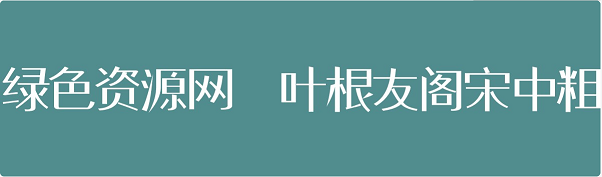
葉根友閣宋中粗是一款使用非常流行廣泛的葉根友字體軟件,字體筆直流暢形體端正,常用于美工設(shè)計(jì)和印刷打印等多種領(lǐng)域,下載安裝即可使用。綠色資源網(wǎng)誠(chéng)意推薦。
葉根友閣宋中粗是一款正文字體,葉根友閣宋微粗適合用于時(shí)尚品牌,廣告海報(bào)標(biāo)題制作,葉根友閣宋中粗是一款全新視覺的宋體類字體。
葉根友閣宋中粗字體線條感十足,粗細(xì)均勻大方得體,字體美感十足廣泛用于創(chuàng)作設(shè)計(jì)字體也能美美噠